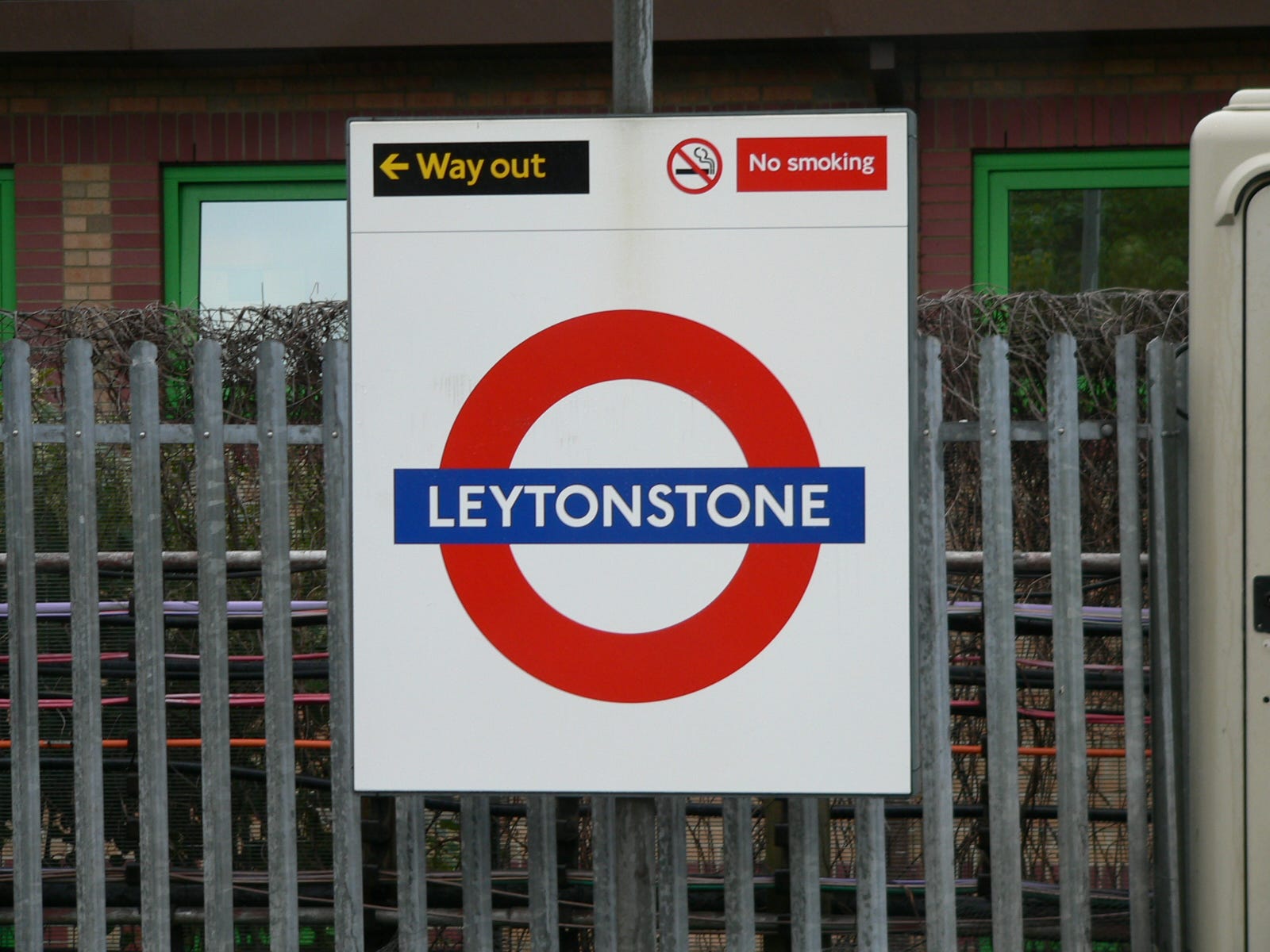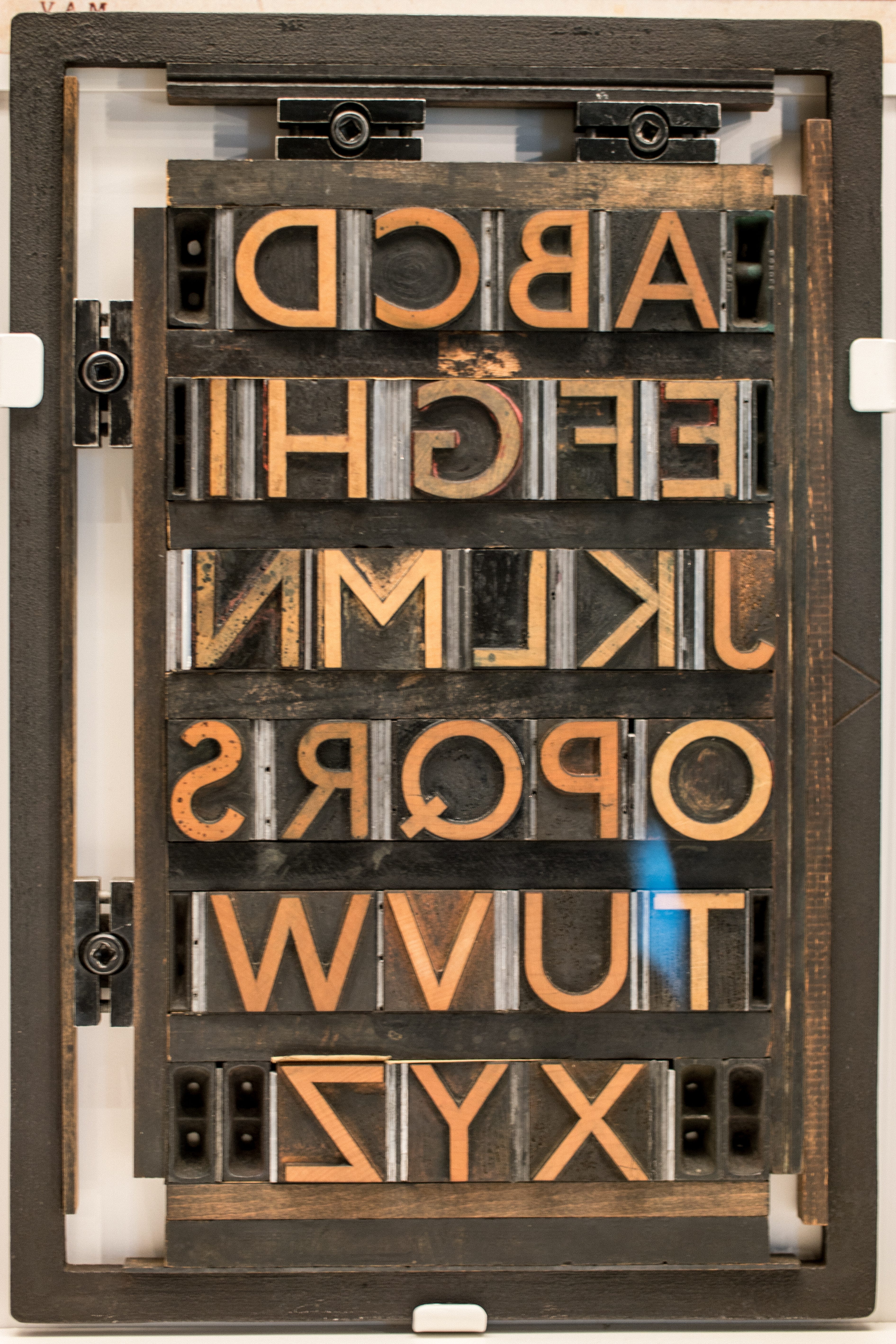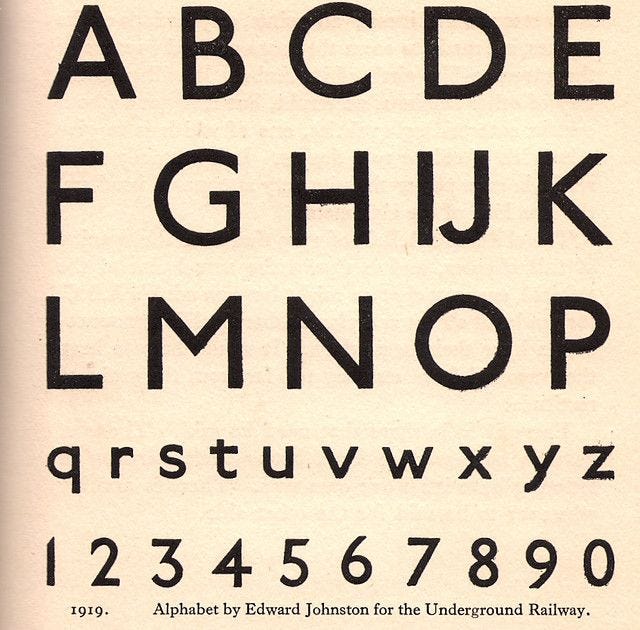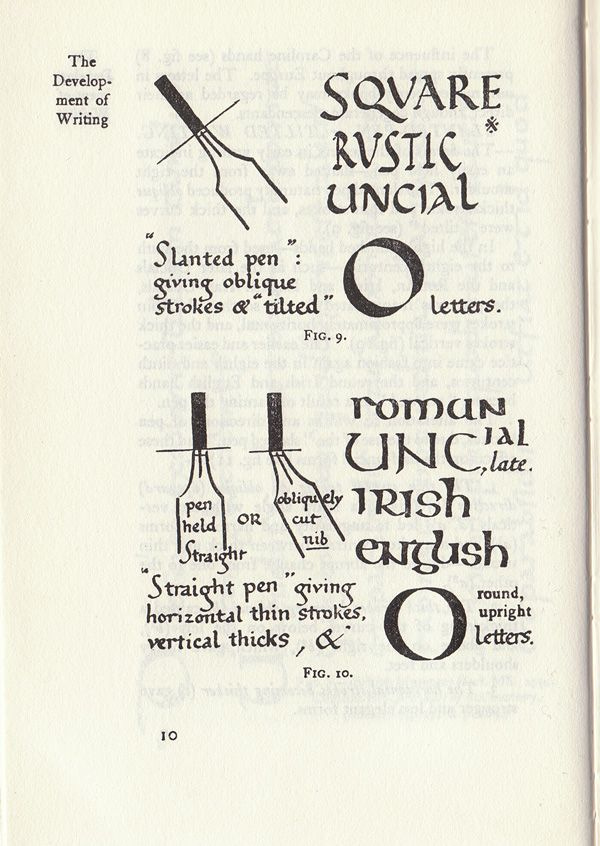
Tipo Aquilo #53 – Johnston, o metrô e as letras fundamentais
As duas grandes revoluções que transformaram a sociedade envolvem, em algum nível, automação e repetição em série de processos de produção: a revolução cultural propagada pela prensa tipográfica de Gutenberg e a revolução industrial desencadeada pela máquina a vapor de Watt e Boulton. Em cinco séculos, elas mudaram o mundo em uma velocidade nunca vista na história, modificando pra sempre unidades fabris, paisagens urbanas e até o modo de vida das pessoas. Tantas foram essas mudanças, que várias pessoas questionaram se essa mecanização da indústria poderia voltar-se contra a sociedade de alguma forma, e se não seria importante manter um grau de manualidade em algum aspecto da vida.
No campo do design, a prensa tipográfica teve diversas evoluções que tornaram-na indispensável para a produção gráfica, deixando a caligrafia em segundo plano, restrita à atividade corriqueira de escrever das pessoas. No começo do séc. XX, houve um resgate das tradições caligráficas que influenciou a tipografia e o design gráfico. Atualmente, mesmo com a presteza e versatilidade da tipografia digital, a caligrafia é uma ferramenta imprescindível para o estudo da tipografia e do lettering, e uma forma de expressão textual e artística que conta com uma autenticidade ímpar. Para entender esse resgate da caligrafia e como ela ganhou de volta essa importância no design gráfico, precisamos falar de Edward Johnston.
Antes de falar de Johnston e da caligrafia fundamental, é importante dar um contexto e começar por William Morris e o movimento de Artes e Ofícios na transição do séc. XIX para o séc. XX, do qual foi um notório representante. Morris, inicialmente, partilhava da crítica à industrialização do arquiteto John Ruskin, alegando que as relações predatórias de trabalho da época e a preocupação excessiva com ornamentação em vez de praticidade resultavam em produtos de qualidade inferior e mau gosto. Ruskin persistiu desencantado com a industrialização, enquanto Morris rendeu-se às maquinas e processos industriais quando conseguiu atingir o padrão de qualidade que sempre desejava… digamos que traiu o movimento, véio!!
Pro bem da verdade, o uso de maquinário industrial per se não era um consenso entre os designers do Arts and Crafts; a divisão de trabalho dentro das fábricas era uma crítica mais consensual. Eles prezavam que todos os envolvidos na fabricação de um produto, entre designers, montadores e outros, fossem exímios conhecedores do ofício de trabalho em madeira, em contraponto à lógica industrial de que cada colaborador só precisa exercer uma função específica da cadeia de produção. Essa relação precária de trabalho gerava, no fim das contas, uma intensa desigualdade social e um sentimento de desencanto com a industrialização da sociedade. Enquanto o cunho social(ista) do Arts and Crafts é pouco comentado, o movimento é conhecido nos dias atuais pelo apego à preservação das artes manuais e o uso delas na arquitetura e design.
Enquanto os designers e arquitetos do Arts and Crafts discutiam o quanto um designer devia ser responsável pela manufatura direta de um produto ou ambiente, Johnston crescia na casa de suas tias. Nascido em San Jose de Mayo, Uruguai, foi trazido com sua família para a Inglaterra aos três anos. Fowell Buxton Johnston, seu pai, estava sempre fora, à procura de emprego; sua mãe, Priscilla Buxton, vivia doente e morreu alguns anos depois. Suas tias tinham forte tendência à germofobia, por isso ele nunca pôde divertir-se fora de casa como as outras crianças; em vez disso, ele se divertia estudando iluminuras, textos medievais escritos à mão com letras capitais ilustradas. De vez em quando, ele até criava as suas próprias iluminuras, copiando o estilo das ilustrações e estudando a caligrafia utilizada.
Além de artes, Johnston também era afeito a matemática e tecnologia. Depois de terminar o ensino básico, chegou a estudar medicina em Edinburgh, mas a paixão pelas artes falou mais alto e buscou a carreira artística. Em 1898, suas iluminuras ganharam o interesse do arquiteto William Richard Lethaby, que foi contemporâneo de Morris e, dentro do Arts and Crafts era adepto da ideia de o designer devia ter pleno conhecimento dos processos de produção e ser capaz de produzir um produto por si. Lethaby era diretor do Central School of Arts and Crafts, e incentivou Johnston a estudar as iluminuras presentes no British Museum e, no ano seguinte, dar aulas de letreiramento em sua escola.
Ao estudar as iluminuras do Museu Britânico, Johnston sentiu-se impelido a treinar caligrafia com pena quadrada. Em 1901, ele passou a dar aulas no Royal College of Art, influenciando diversos designers de sua época e resgatando a tradição das letras escritas à mão, algo que vinha sendo perdido desde a massificação da tipografia na Inglaterra. Em 1906, lançou o livro Writing & Illuminating & Lettering, um compêndio de seus estudos sobre iluminuras; no entanto, com o tempo, ele mudou o foco de seus estudos para a caligrafia. Além das formas das letras, Johnston dava grande atenção às suas proporções, sendo influenciado por manuscritos renascentistas, que continham exemplares de letras romanas.
Esse estudo das letras romanas fez com que, com o tempo, ele criasse um estilo de letra voltado para o ensino e introdução de novatos à caligrafia com pena quadrada, as letras fundamentais. Influenciada também pela caligrafia meio-uncial e as minúsculas carolíngias, as letras fundamentais têm formas simples, com poucos ornamentos, e são a porta de entrada para todos que estudam e trabalham com as formas das letras. Estudar e praticar a caligrafia de Johnston dá experiência com uma pena caligráfica e noções de contraste e espaçamento que são fundamentais (rá!) para qualquer caminho que a pessoa siga, seja projetar tipos, escrever com outros estilos caligráficos ou ilustrar com letras. Por isso, 10 entre 10 calígrafos recomendam a foundational hand como porta de entrada para drogas mais fortes. ;)
A influência de Johnston vai além do resgate da arte da caligrafia; ele também é responsável pela primeira família tipográfica corporativa para um projeto de identidade visual. Quem já teve a oportunidade de andar pelo sistema de transporte público em Londres passou por placas, letreiros informativos e outros impressos que usam a fonte que Johnston projetou de 1913 a 1916 para a companhia de trens elétricos subterrâneos, o famoso London Underground. As letras projetadas por Johnston, mesmo sem serifas, são frutos diretos de seus estudos de caligrafia, e inauguraram uma nova classificação de fontes, as humanistas sem serifa (como a Optima, Verdana e a Freight Sans), que combinam as proporções das letras romanas com um desenho elegante, sem serifas e com contraste quase nulo. Em 1933, a Johnston tornou-se a família tipográfica padrão do sistema de transporte público londrino, e assim permanece até hoje.
O trabalho de Edward Johnston teve grande influência entre designers, calígrafos e tipógrafos, como Stanley Morrison, Graily Hewitt e Florence Cockerell, que reconheceram em seus estudos de caligrafia e letreiramento uma alternativa para a produção de peças mais refinadas e autênticas, trazendo para a tipografia um pouco do que o movimento de Artes e Ofícios de Morris ensejava para o mundo. Era comum, em seu tempo, que se alguém perguntasse a um inglês quem inventou a caligrafia, o nome de Edward viesse à lingua num estalo. Junto com o alemão Rudolf Koch (de quem pretendo falar em breve), Johnston é considerado o pai da caligrafia moderna, e suas letras seguem vivas até hoje pelas ruas e túneis de Londres. (=